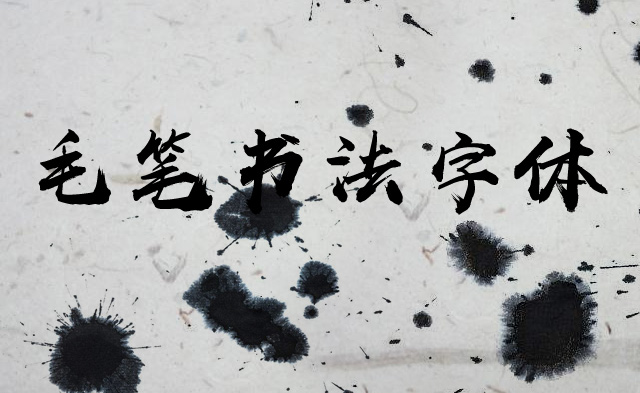
毛笔书法是中国特有的一种传统艺术。古往今来,中国汉字是劳动人民创造的,开始以图画形式表示文字,经过几千年的发展,演变成了当今的文字,古代长期用毛笔写字,便产生了书法。均以毛笔书写汉字为主,至于其他书写形式,其书写规律与毛笔书写规律相比,并非迥然不同,而是基本相通。这里重点介绍毛笔书法。
毛笔书法现在一共有六种书体,即行书体、草书体、隶书体、篆书体、楷书体和马书体六种书体书法。
判断书法作品的优劣主要通过字体的线条,流畅性,还有整体性。中国是书法艺术文化的发源地,也是最早使用毛笔的国家。
我国毛笔书法家层出不穷,像王羲之,颜真卿,怀素,苏东坡,黄庭坚,米芾,王铎,柳公权,以及近代的沙孟海,启功,刘惠浦等,这些文学雅士都是功力高深的书法大家。毛笔书法艺术需要我们后一辈发扬光大,我们需要努力。
毛笔书法分类
中国书法是中国特有的一种传统艺术,主要分为“软笔书法”和“硬笔书法”。古往今来,中国汉字是劳动人民创造的,开始以图画记事,经过几千年的发展,演变成了当今的文字,又因祖先发明了用毛笔书写,便产生了书法,古往今来,均以毛笔书写汉字为主,至于其他书写形式,如硬笔、指书等,其书写规律与毛笔书写规律相比,并非迥然不同,而是基本相通。基于索本求源(指甲骨文之后),这里重点介绍毛笔书写汉字的规律。只要我们对书法有了“狭义”的理解,那么对领会“广义的书法”也会大有裨益。
从狭义讲,书法是指用毛笔书写汉字的方法和规律。包括执笔、运笔、点画、结构、布局(分布、行次、章法)等内容。例如,执笔指实掌虚,五指齐力;运笔中锋铺毫;点画意到笔随,润峭相同;结构以字立形,相安呼应;分布错综复杂,疏密得宜,虚实相生,全章贯气;款识字古款今,字大款小,宁高勿低等。
从广义讲,书法是指语言符号的书写法则。换言之,书法是指按照文字特点及其涵义,以其书体笔法、结构和章法写字,使之成为富有美感的艺术作品,随着文化事业的发展,书法已不仅仅限于使用毛笔和书写汉字,其内涵己大大增加。例如,从使用工具上讲,仅笔这一项就五花八门,毛笔、硬笔、电脑仪器、喷枪烙具、日常工具等种类繁多。颜料也不单是使用黑墨块,墨汁、粘合剂、化学剂、喷漆釉彩等五彩缤纷,无奇不有。过去的文房四宝——笔、墨、纸、砚,其涵义也大有扩展,品种之多,不胜枚举;从执笔方式上看,有的用手执笔,有的用脚执笔,就是用其他器官执笔的也不乏其人,甚至有的人写字根本就不用笔,如“指书”“挤漏书”等;从书写文种上说,并非汉字一种,有的少数民族文字也登上了书法艺坛,蒙文就是一例;从书体和章法上看,除了正宗的传统书派以外,在我国又出现了曲直(线)相同、动静结合的“意向”派,即所谓现代书法。它是在传统书法基础上,加以创新,突出"变"字,融诗书画为一体,力求形式和内容统一,使作品成为“意美、音美、形美”的三美佳作。在日本不少书家摒弃文字的语言性,树立文字的“形象性”,出现了“墨象”派,以用笔的轻重和徐疾、笔锋的开合及落笔位置的变化等,写出各种形象的文字。这一书派,虽突出“意象”,其字赏之也新颖,但汉字并非都是“形象”字,因此步履艰难,发展受到限制。所有这些(当然不仅是这些),可以看出书法和其他事物一样,也是在不断地发展和变化着。这一点必须引起书法界人士的高度重视。